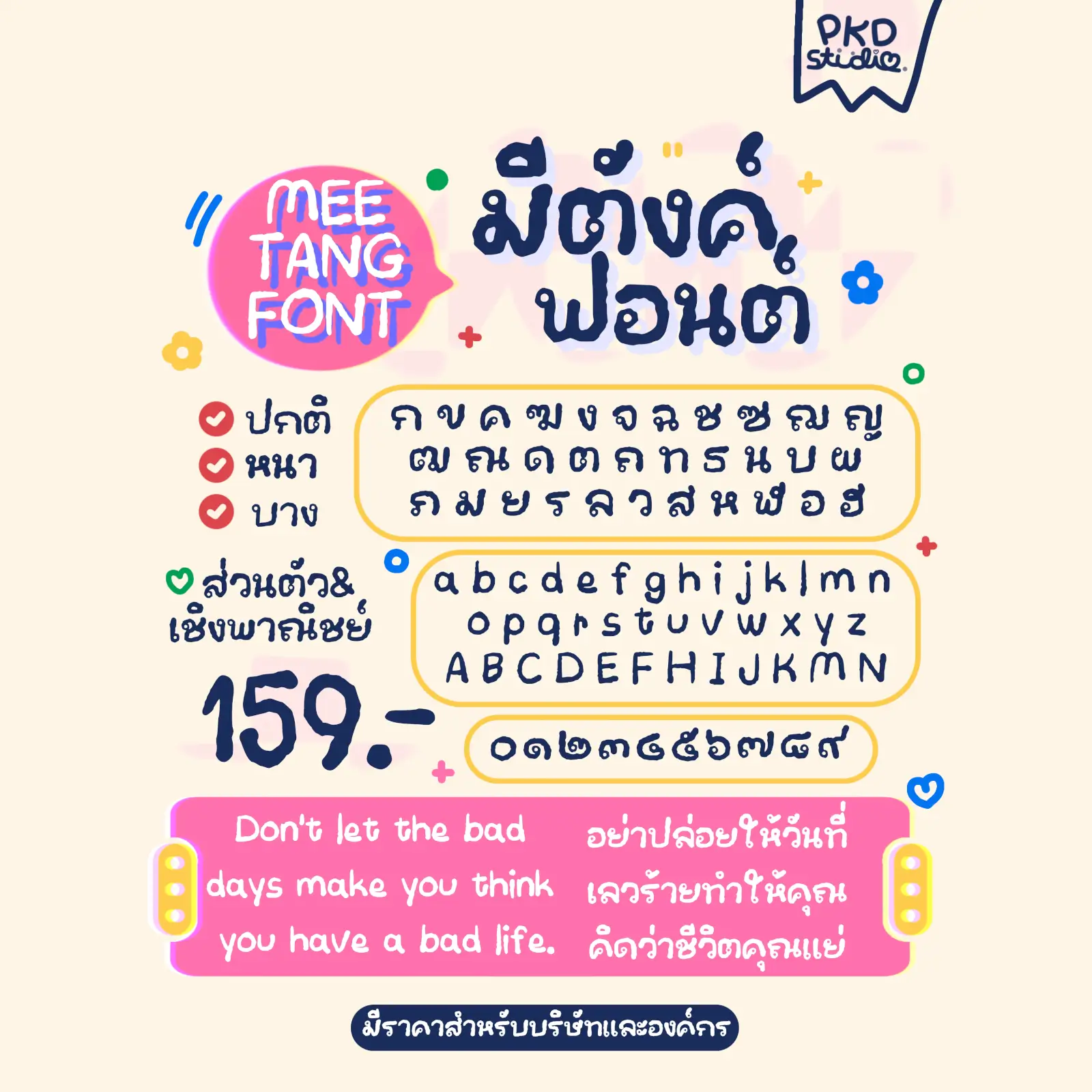
มีตังค์ฟอนต์ (PKD Meetang) – ฟอนต์ลายมือน่ารัก สดใส เป็นกันเอง เหมาะสำหรับงานคอนเทนต์ โพสต์โซเชียล สติกเกอร์ คาเฟ่ และงานออกแบบทั่วไป
- รองรับภาษาไทย ภาษาอังกฤษ ตัวเลข และสัญลักษณ์
มีตังค์ (PKD Meetang)